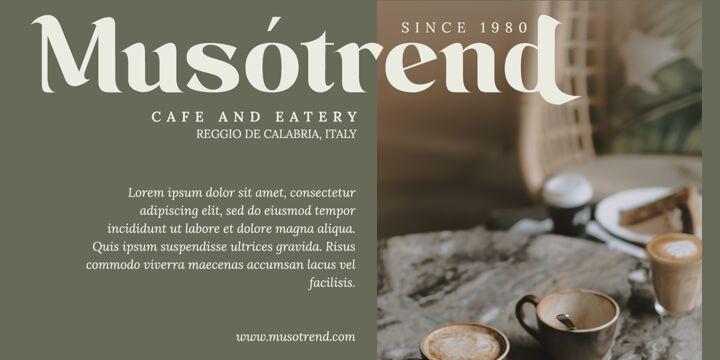
Americana Viktoria Font
Description de Americana Viktoria Font
Présentation d’Americana Viktoria, une police serif – où l’Americana classique rencontre l’élégance de Viktoria. Cette police allie sans effort charme intemporel et sophistication raffinée, ce qui en fait le choix idéal pour les projets qui exigent un mélange de tradition et de modernité. Élevez votre design avec le style polyvalent et distinctif de la police Americana Viktoria Serif.